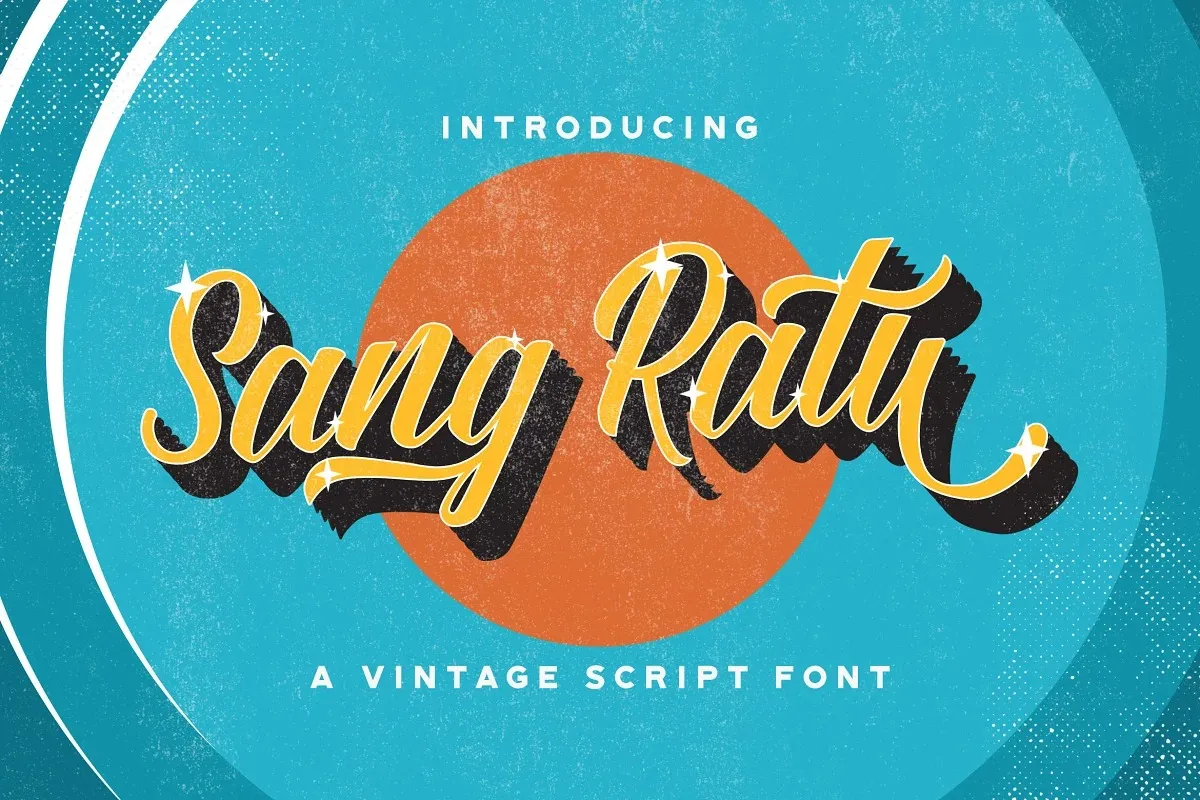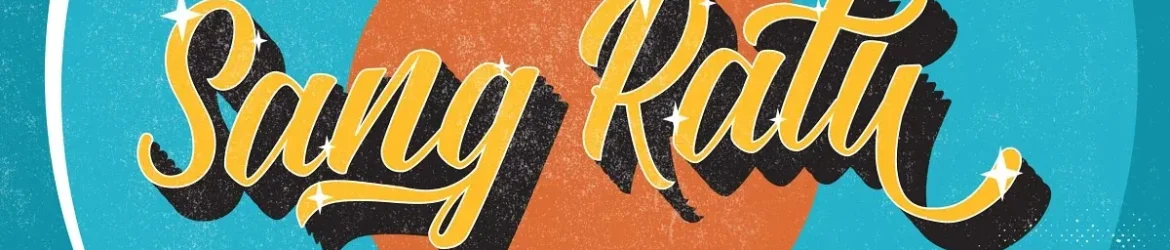
A ‘Sang Ratu Font’ é uma nova adição ao nosso catálogo de fontes script, projetada pelo talentoso designer StringLabs na plataforma 99designs. Esta font tem um estilo único e arredondado, característica que se destaca em sua elegância vintage. Ela é ideal para personalizar marcas e logos com originalidade, dando vida a suas melhores ideias criativas. Com seu traço bold e curvo, a ‘Sang Ratu Font’ traz um toque de nostalgia ao design moderno, tornando-a perfeita para qualquer projeto que busque uma conexão visual única. Seja para criar um novo logo ou reforçar a identidade visual de sua marca, esta font irá destacar seu trabalho e fazer dele algo especial.